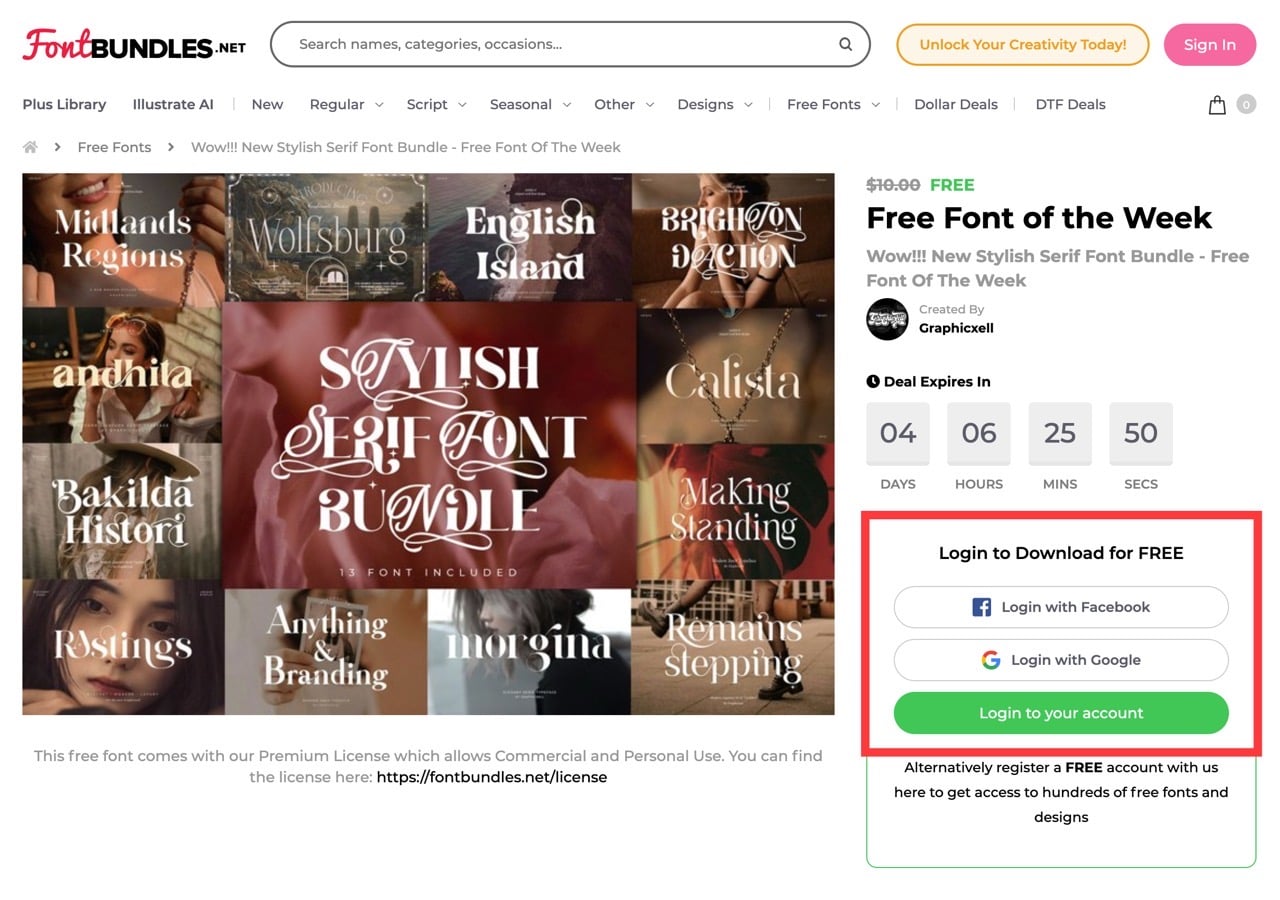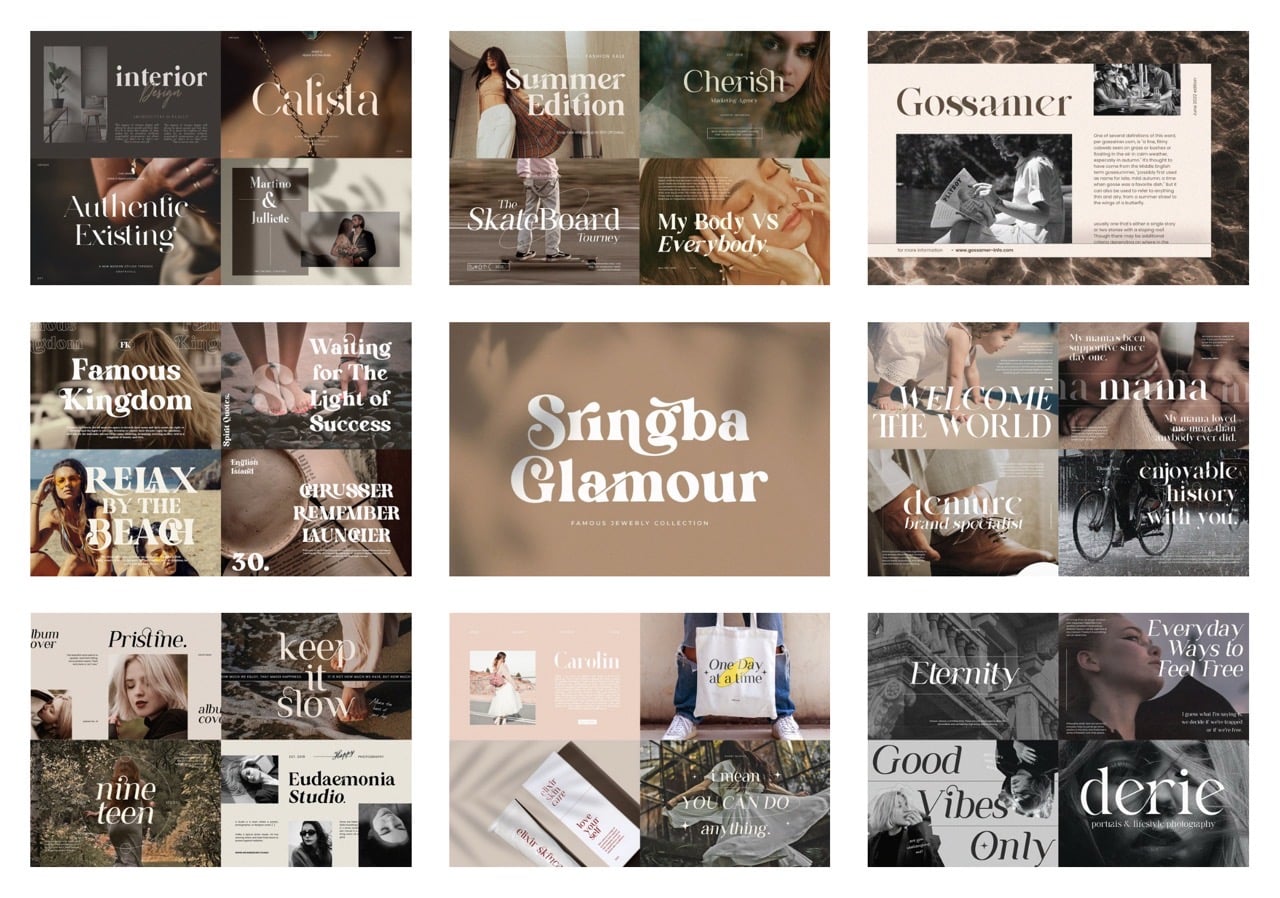
限時免費!Font Bundles 贈送 New Stylish Serif 字型包(含 11 款精美襯線字體)
Font Bundles 限時免費:New Stylish Serif Font Bundle 11 款襯線字型包下載
國外 Font Bundles 網站每週都會帶來一套免費字型組合,本週限免活動(Free Font of the Week)贈送的字型包來自印尼設計工作室 Graphicxell,這套名為「New Stylish Serif Font Bundle」字型包主要收錄一系列具有現代感且風格獨特的襯線字體(Serif),設計相當精美,很適合使用於品牌形象、Logo 設計或時尚雜誌排版。
New Stylish Serif Font Bundle 收錄清單
• Brighton Daction
• Midlans Reguions
• Andhita
• Bakilda Histori
• Rastings
• Anything Branding(本次未提供)
• Morgina
• Remains Stepping
• Making Standing
• Calista
• English Island
• Wolfsburg